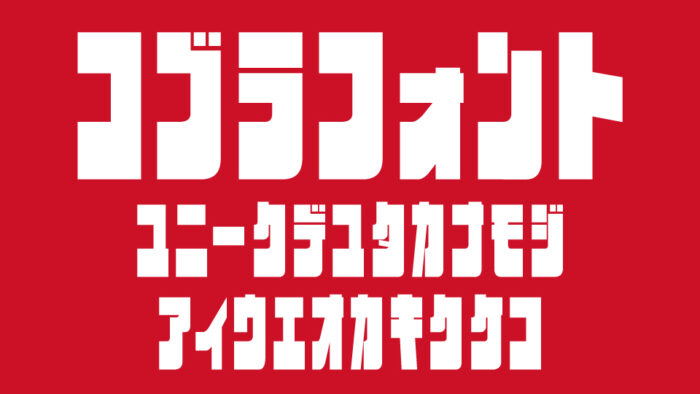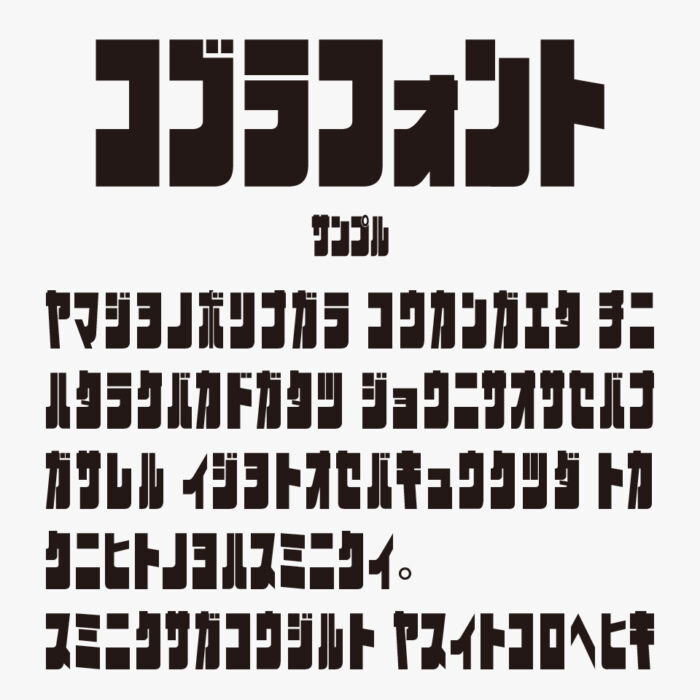
コブラフォントアドベンチャー
コブラフォントは、アニメ「スペースコブラ」のロゴをヒントに制作されたカタカナフォントです。
極太で密度のあるシルエットが印象的な、重厚感とインパクトを兼ね備えたフォントです。角のとれたスクエア型の骨格と、ぎゅっと詰まった文字の配置が、「スペースコブラ」のような力強くてどこか無骨な雰囲気を生み出しています。